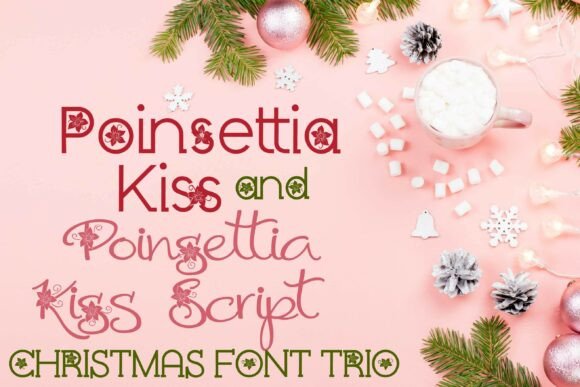
Poinsettia Kiss Trio
適切なデザイン要素を見つけるのは難しい場合がありますが、Poinsettia Kiss Trioは作品を即座に引き立てる優れたコレクションを提供します。
POD(オンデマンド印刷)製品、結婚式の招待状、またはソーシャルメディアのグラフィックを作成している場合でも、Poinsettia Kiss Trioは理想的です。